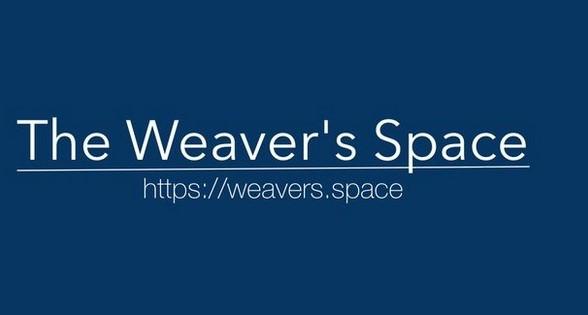
Suche nochmal eine Schrift
Was könnte das sein?
Avenir.
Mit falschem Apostroph, aber das sei in einem Logo erlaubt ;-)
Wer weiß, vielleicht ist es ja der Space von einem Typen, der als The Weaver bekannt ist? :-?